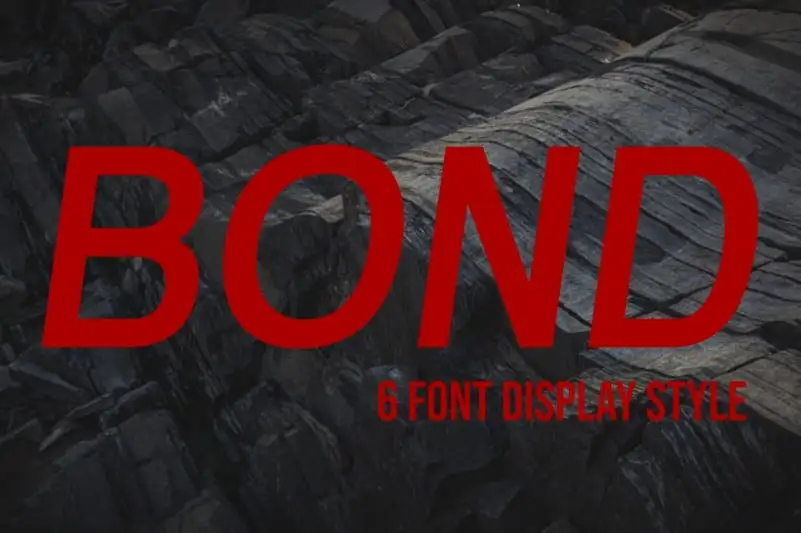
Bond Sans Serif Font – Download Grátis
Bond Sans Serif Font é uma tipografia sans-serif que transmite força e poder através de sua forma condensada e distinta. Inspirada na personalidade assertiva de indivíduos notáveis, essa fonte exibe traços sóbrios e texturas suaves, criando um contraste interessante entre o robusto e o sedoso. Suas formas simples são o distintivo dessa família de fontes. Ainda que minimalista, a Bond Sans Serif mantém um valor estético, tornando-a uma escolha perfeita para designers que procuram simplificar temas sem perder elegância. Este é especialmente útil em designs com simplicidade e destaca-se como uma opção versátil em vários contextos de uso.